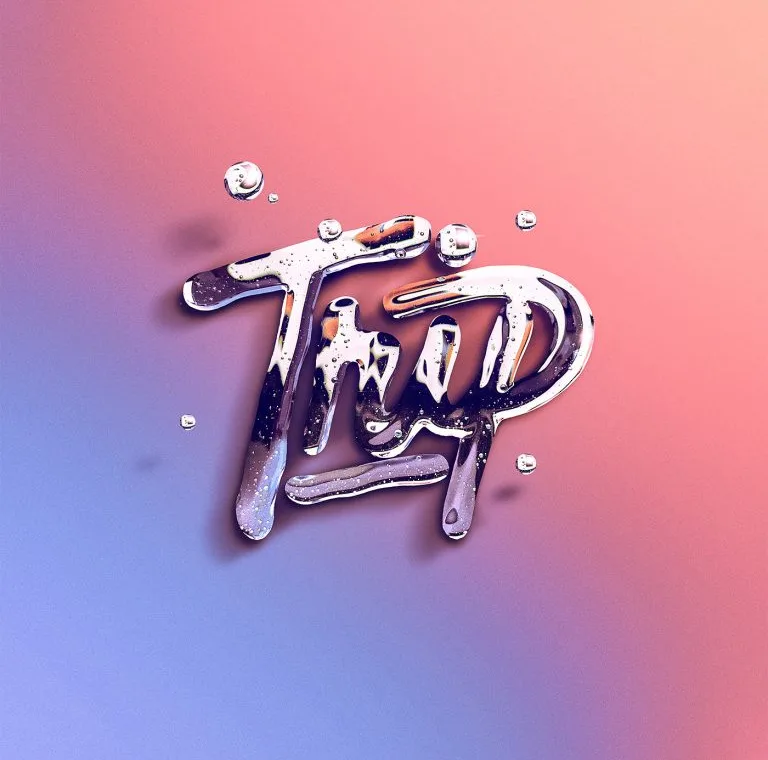
Designer cria e inspira a criação de diversos estilos de tipografia
David Milan tem desenvolvido diversas tipografias inspiradas em várias situações, artistas e afins.
O artista até confirmou que faz a criação de diversos estilos e que se sente feliz e ao mesmo tempo como se pudesse ser diversos artistas diferentes, sem precisar ter um único estilo.
Suas tipografias são tão variadas e ao mesmo tempo tão criativas, que acompanhá-lo poderá lhe fornecer diversos tipos de inspiração.